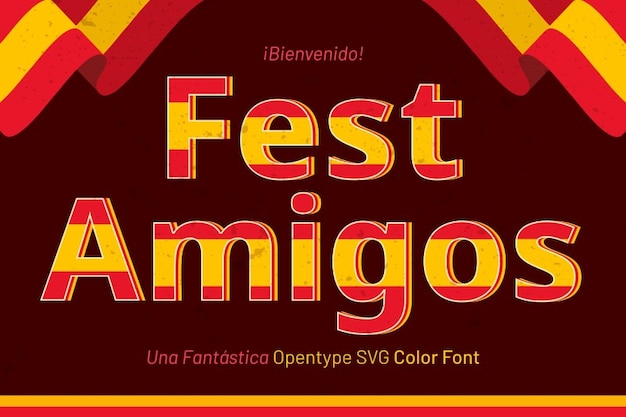
Fest Amigos 폰트
Fest Amigos는 굵은 3D 문자와 생동감 넘치는 스페인 국기 색상으로 축제의 정신을 담아낸 활기 넘치고 축제 분위기의 폰트예요. 역동적인 형태와 쾌활한 분위기 덕분에 파티 테마 디자인, 문화 행사, 활기찬 에너지와 국가적 자긍심을 불러일으키는 모든 것에 완벽하게 어울려요.